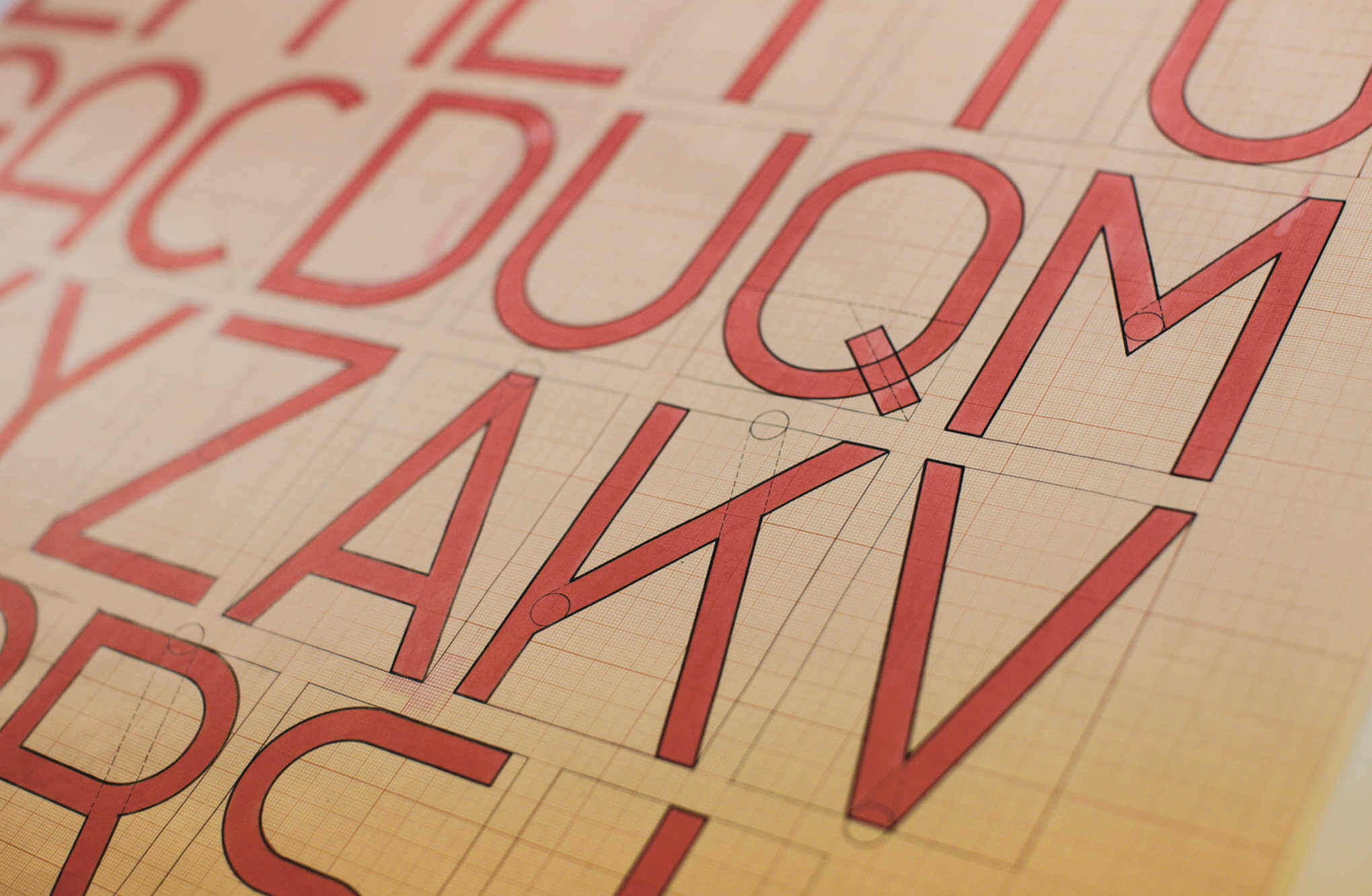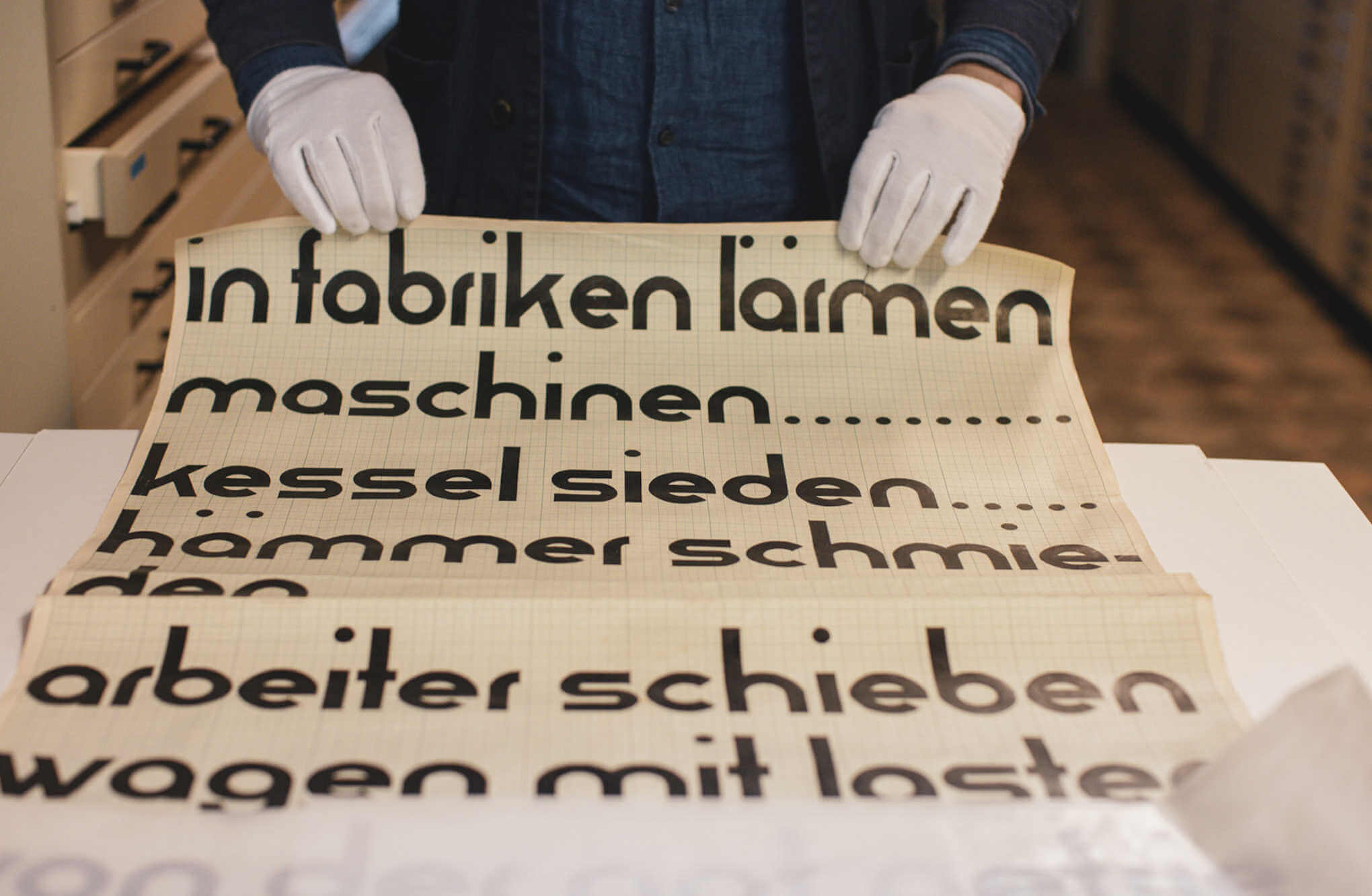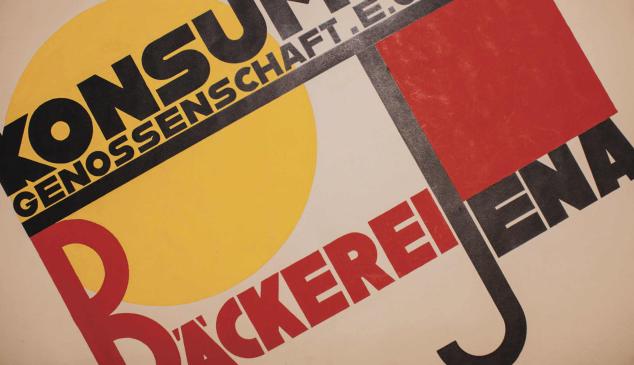
Adobe continúa desenterrando tesoros. El año pasado recreaba y digitalizaba los pinceles de Edvard Munch. Ahora ha recuperado las tipografías de la famosa escuela de diseño Bauhaus Dessau: “Los Alfabetos perdidos de la Bauhaus Dessau”.
Los Alfabetos de Bauhaus Dessau
La iniciativa forma parte del proyecto Hidden Treasures of Creativity (Tesoros escondidos de la creatividad). Con esta acción traen a la vida las tipografías inacabadas que hace casi 100 años diseñadores legendarios de la Bauhaus iniciaron. Un nuevo recurso traído del pasado a través de bocetos y fragmentos de letras para inspirar a una nueva generación de artistas.
Bauhaus Dessau, la mundialmente reconocida escuela de diseño, fue cerrada en 1932 por el Partido Nacional Socialista. Su cierre dejó obras maestras inacabadas de legendarios maestros del diseño, nombres como Xanti Schawinsky, Joost Schmidt, Carl Marx, Alfred Arndt y Reinhold Rossig. En colaboración con la Fundación Bauhaus Dessau, Adobe se propuso completar y digitalizar el trabajo interrumpido de estos diseñadores y finalizar las tipografías para convertirlas en históricas fuentes a disposición de los usuarios.
Erik Spiekermann, diseñador de tipografías de reconocido mundialmente, ha sido el responsable de convertir estos fragmentos y bocetos descubiertos en completos pack de fuentes para Typekit.
Spiekermann ha liderado y dirigido un equipo internacional de profesionales de la tipografía y estudiantes de diseño que con gran esfuerzo han realizado los cálculos detallados para extraer las probabilidades de las formas hasta deducir cómo los Maestros planeaban diseñar originariamente estas tipografías.
Con estos datos y Adobe Illustrator, el equipo completó y digitalizó las fuentes de las cinco leyendas del diseño.